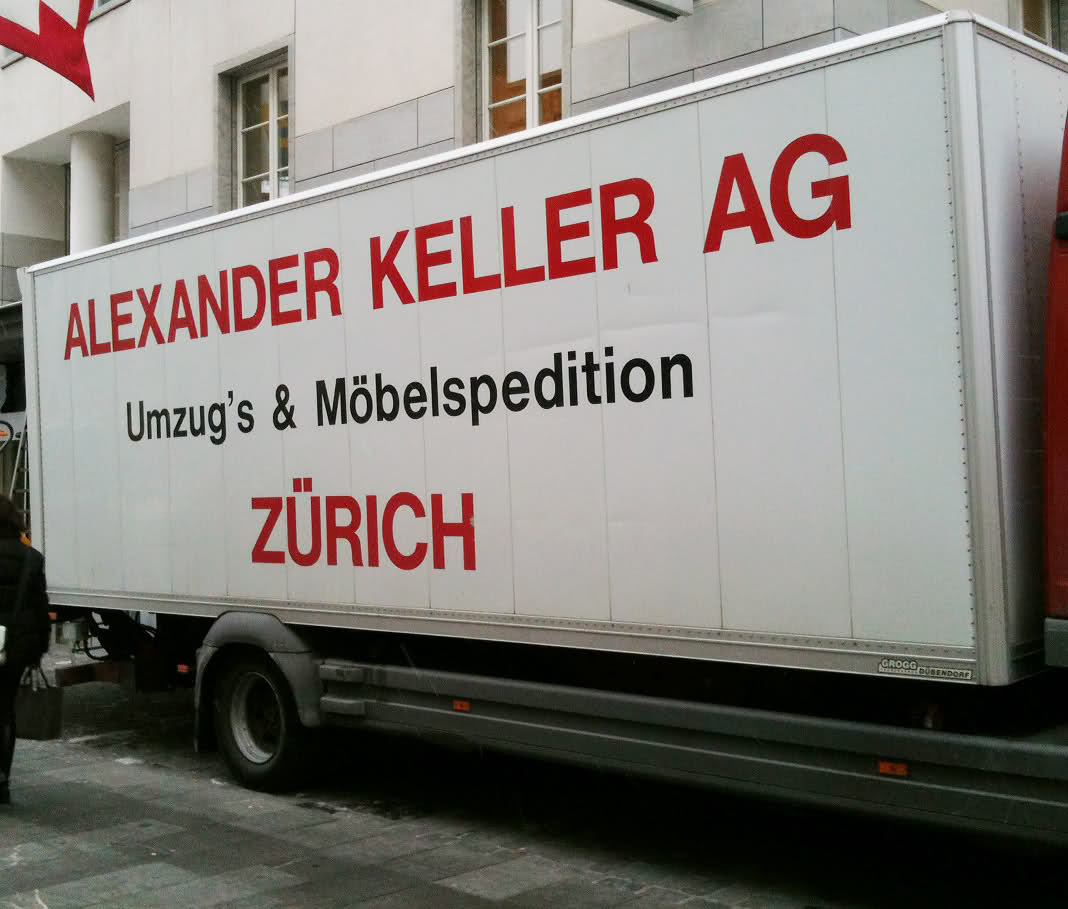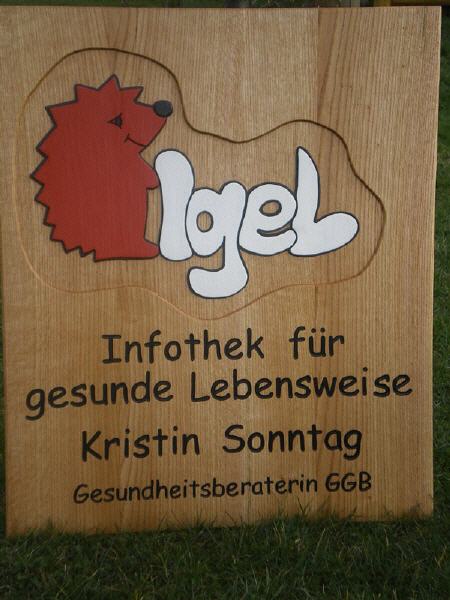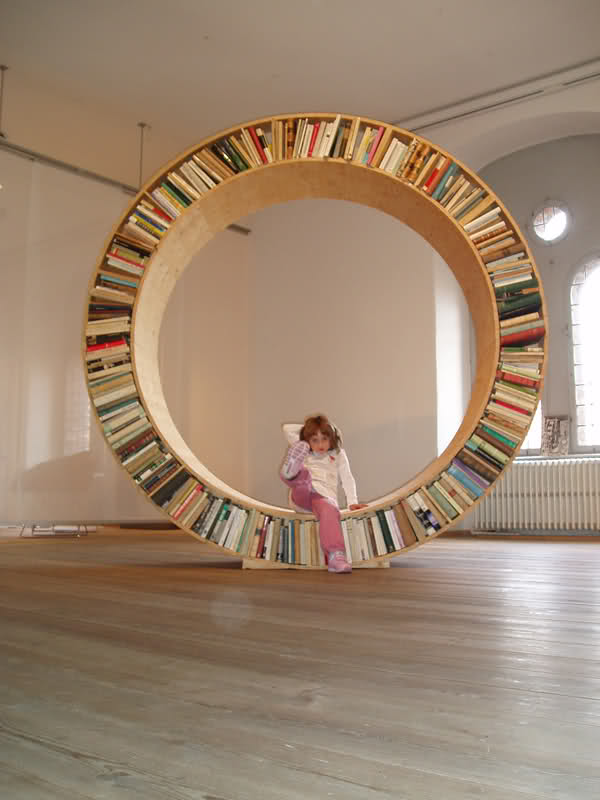
Ich stell mir grad den Setzerlehrling vor, der geschickt wurde, eine Dose Futura zum Nachfüllen zu holen. Und dann kommt er wirklich mit einer an … :lol:
So sehen übrigens die Wegweiser für Wanderer und Radfahrer auf Mallorca aus … :-|
Diese Schrift lässt sich offensichtlich sogar mit dem Lötkolben in Holzschilder brennen …
Das ist bestimmt gelasert. Für Lötkolben sieht mir das zu homogen aus. Die, äh, sagen wir mal großzügige Sperrung auf dem unteren Schild ist in dieser Schrift™ auch sehr eindrucksvoll.
Die Sperrung steht doch ganz klar für die Entfernung: 30 Minuten weg: kaum gesperrt – 1,5 Stunden Weg: große Sperrung ;-)
Wenn bei anderthalb Stunden schon ein reichliches Geviert dazwischengeprügelt wurde, wie hat man sich dann das Schild vorzustellen, das auf einen Tagesmarsch verweist? :mrgreen:
Das ist bestimmt gelasert.
Weiß zwar nicht ob mit Lötkolben (eher nicht) aber trau mich zu wetten, das ist handmade.
Tja, ich weiß es nicht. Aber von den Schildern gibt es so irre viele auf der Insel, dass ich mich (entgegen meiner ersten Annahme) frage, ob das mit der Hand überhaupt zu schaffen ist. Da ist Pachulke vermutlich eher auf der richtigen Spur mit dem Lasern.
Da ist Pachulke vermutlich eher auf der richtigen Spur mit dem Lasern.
… auch wenn gleich Buchstaben unterschiedlich aussehen?
Ich denke dass die gefräst und dann angemalt sind. So wie dieses, um bei der Comic zu bleiben …
Wenn bei anderthalb Stunden schon ein reichliches Geviert dazwischengeprügelt wurde, wie hat man sich dann das Schild vorzustellen, das auf einen Tagesmarsch verweist? :mrgreen:
Da gibt’s dann Panoramaschiler, die am ganzen Weg entlang laufen. Daher braucht man dann auch nur ein einziges Schild für die ganze Rute ;-)
… Schild für die ganze Rute ;-)
Ein Schild für die Rute und das, was vorne an der Rute dranhängt ;-)
... und, wenn’s dann doch passiert, gibt’s das hier:
Meine Frau hatte gerade diese minimalistische Typo-Krippe entdeckt:
Okay, es ist ja nur die UBS, die hier und heute mit so Umzug’s beliefert wird, aber trotzdem …
Um das Thema »Buchstaben als Möbel« mal wieder zum Leben zu erwecken: Der niederländische Designer Pieter de Leeuw hat ein Regalsystem entwickelt, das komplett aus Buchstaben besteht. Jeder Buchstabe kostet 199 Euro. www.deleeuwdesign.nl
Ja allerdings – für den Wert eines solches Buchstaben kann man sich schließlich schon eine komplette Schriftfamilie kaufen. Da weiß ich auch, wie meine Kaufentscheidung ausfallen würde. Aber schön ist das Regal trotzdem. ;-)
Um das Thema »Buchstaben als Möbel« mal wieder zum Leben zu erwecken …
Ein O, 2009 im Rundetårn gesehen :-)
Das ist soooo schön! Das hast Du uns doch vor langer Zeit schon mal im Buchstabenthread gezeigt, richtig? Allerdings nicht so schön groß. So ein Regal hätte ich auch gerne … :biglove:
Voll schön. Gleichzeitig Bücherregal und Sitzgelegenheit. *Will auch haben*
Hatten die auch andere Buchstaben?
… Hatten die auch andere Buchstaben?
Nö, aber noch andere Möbel. Kann ich heute abend gern Bilder hochstellen :-)